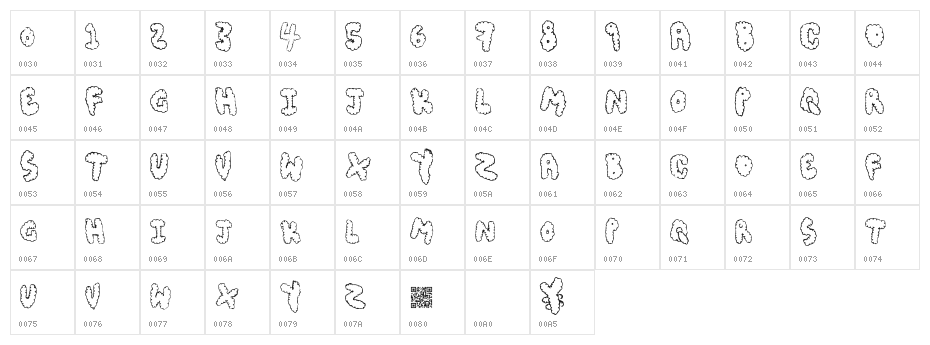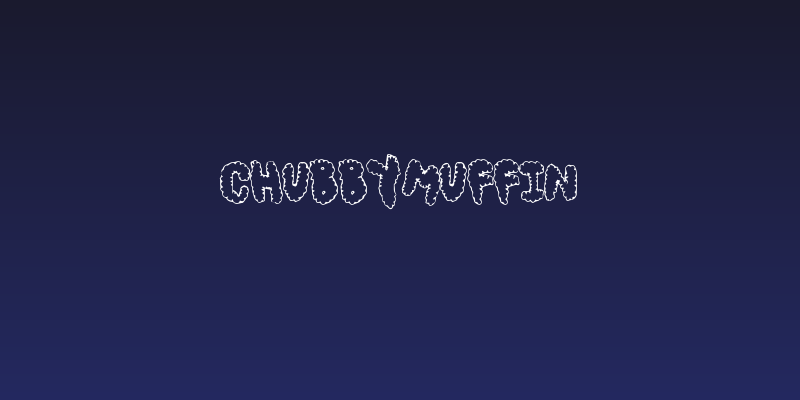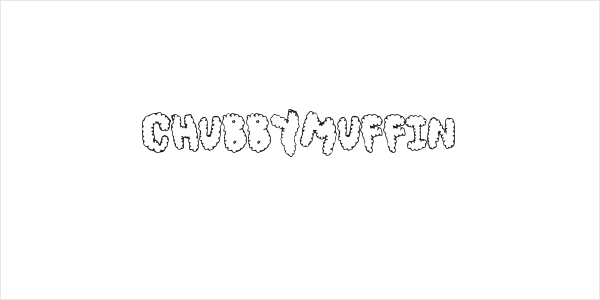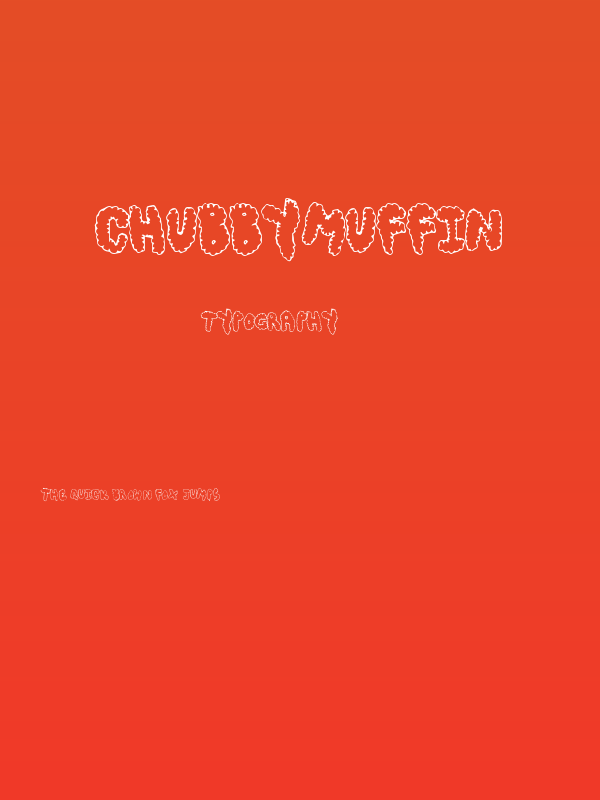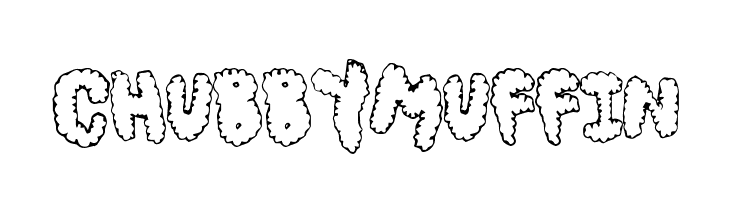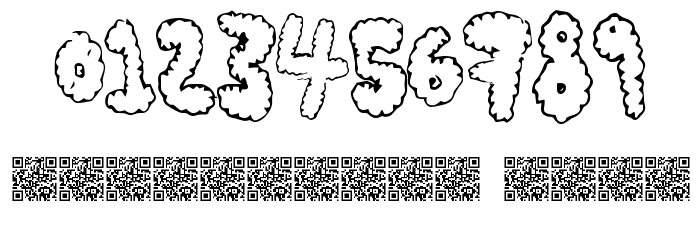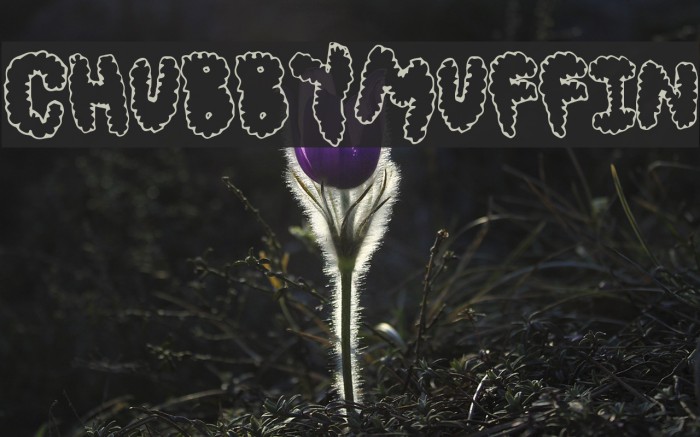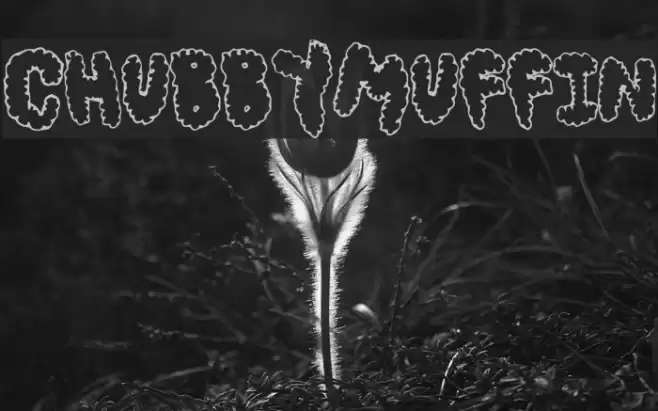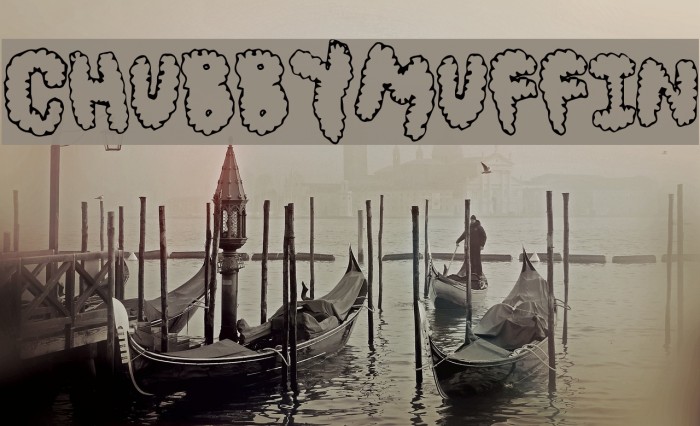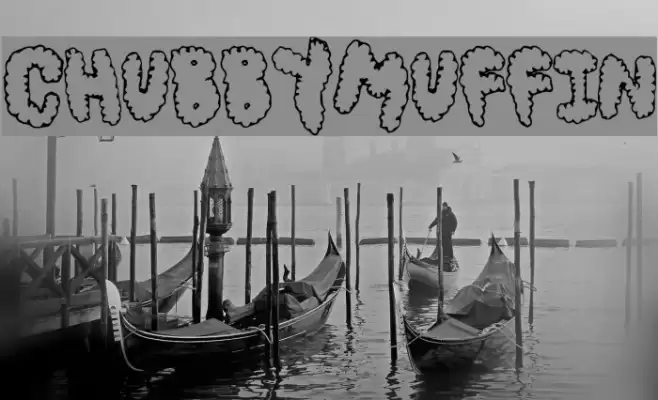
ChubbyMuffin Font
| Vorgeschlagene Projekte | Ideal for children's book covers, playful branding, party invitations, or any project that requires a fun and whimsical touch. |